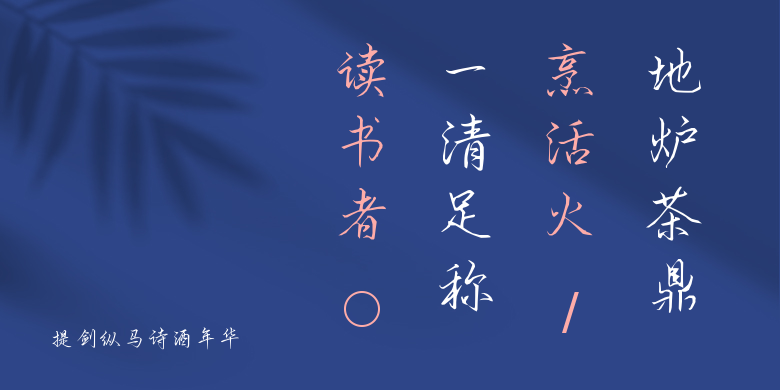
提剑纵马诗酒年华
提剑纵马诗酒年华,这款字体结构工整、笔画清晰,兼顾美观与易读性,适用于标题、正文、海报、包装、LOGO 等多种场景。字形优雅稳定,风格百搭耐看,适配日常排版与创意设计,让文字呈现更舒适、更具质感。提剑纵马诗酒年华一笔一画,皆是细节,以均衡的比例、流畅的线条打造舒适视觉体验,字形端正大气,风格简约现代。无论是商业设计、品牌宣传还是日常排版,都能轻松驾驭,让文字更有格调与力量。提剑纵马诗酒年华字体下载。